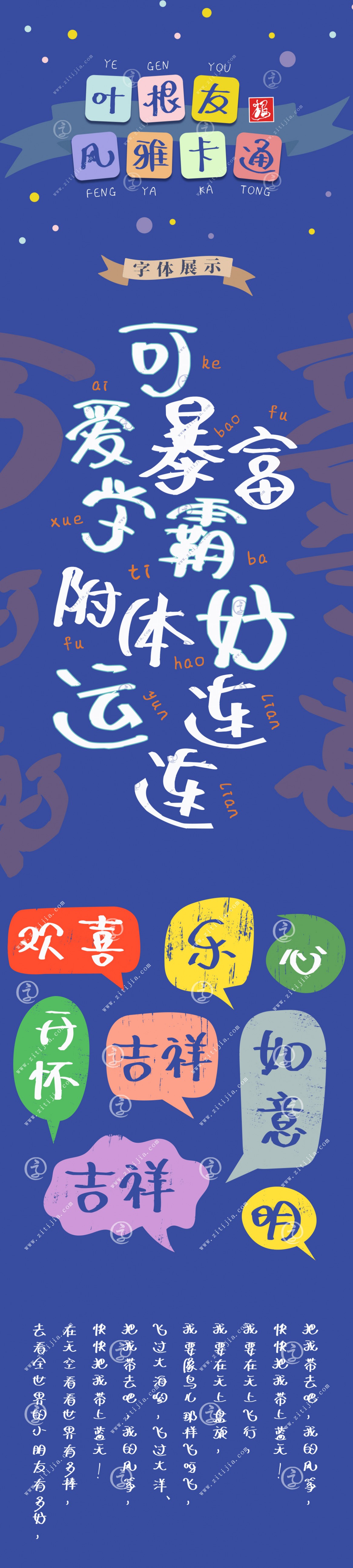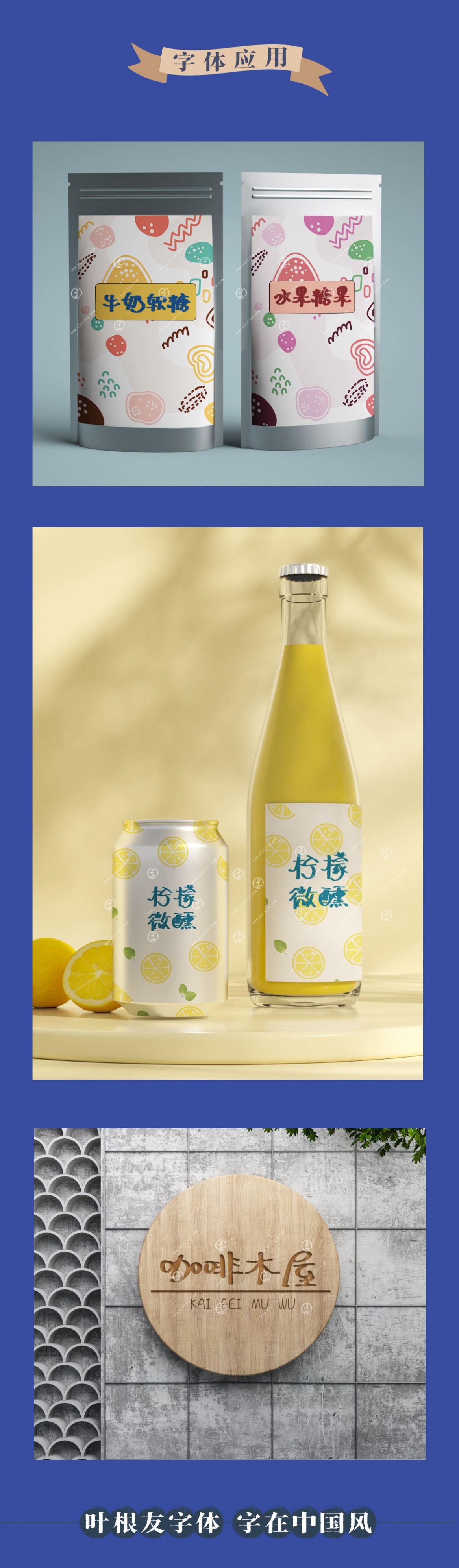
葉根友風(fēng)雅卡通
葉根友風(fēng)雅卡通是葉根友系列字體中的一款創(chuàng)意藝術(shù)體,書(shū)寫(xiě)醒目美觀,靈動(dòng)可愛(ài),有著很好的視覺(jué)感,適合應(yīng)用于藝術(shù)設(shè)計(jì)、平面宣傳設(shè)計(jì)、網(wǎng)頁(yè)設(shè)計(jì),書(shū)法字帖等領(lǐng)域,需要的朋友可以前來(lái)字體家官網(wǎng)下載。